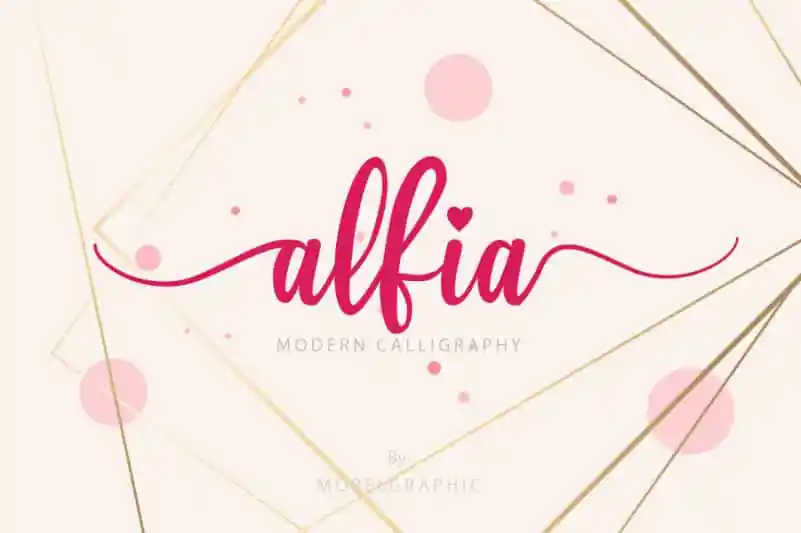
Alfia Calligraphy Font
A Alfia Calligraphy Font é uma escolha perfeita para designers que procuram a essência do estilo calligrafico com leveza e elegância. Esta fonte vem equipada com um conjunto completo de letras maiúsculas e minúsculas, alternativas em swash, ligaduras multilinguas, símbolos, números e marcadores de pontuação. Ela foi criada por Morelgraphic e é perfeita para uma ampla gama de projetos, desde design de convites de casamento até slogans e logotipos. O resultado final impressionará com sua beleza e originalidade, tornando a Alfia Calligraphy Font um recurso indispensável para quem busca transmitir seus ideais de forma única e envolvente em qualquer projeto.
Designer: Morelgraphic